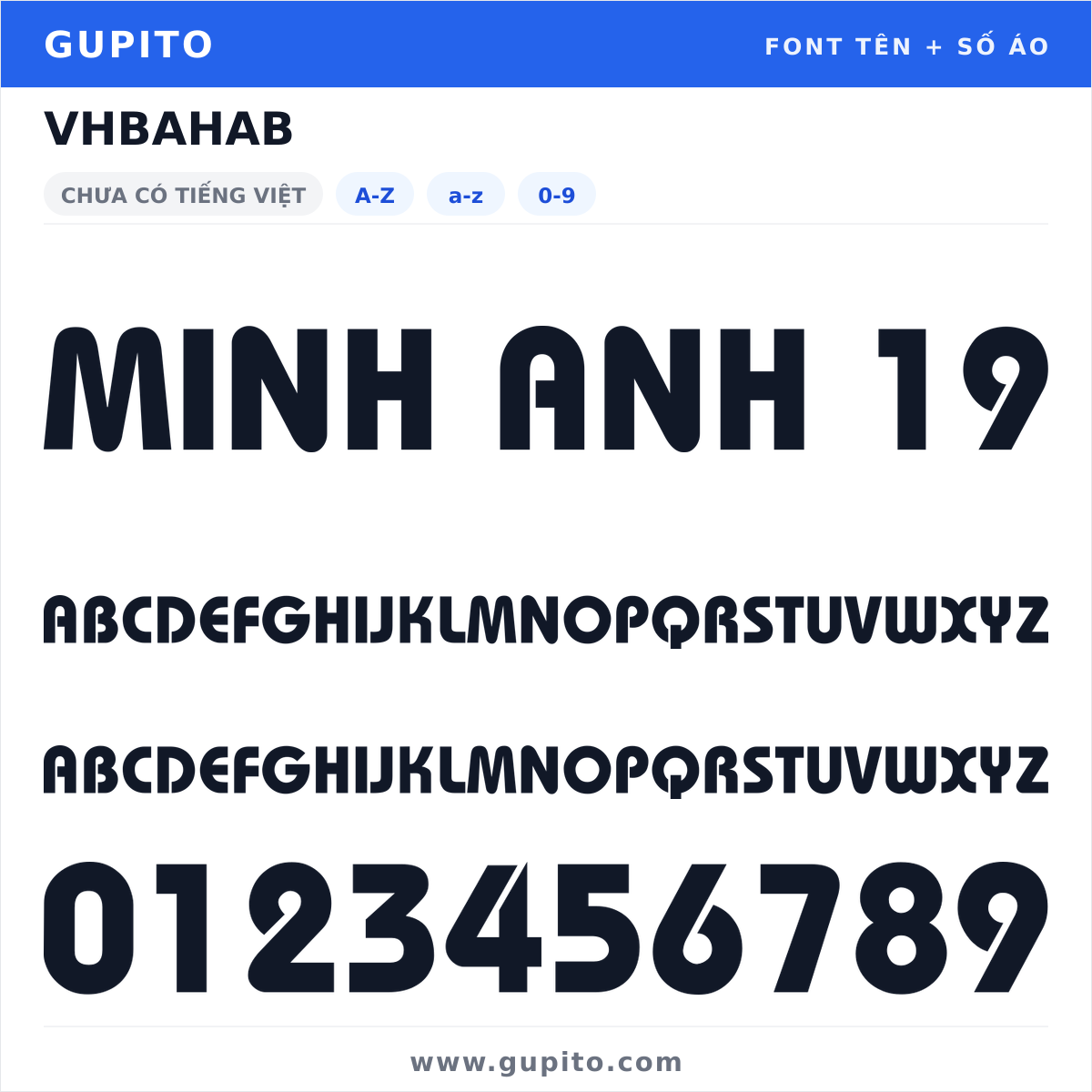
.VnBahamasBH Bold
.VnBahamasBH Bold · Font VHBAHAB in tên số áo thể thao, font chữ in chuyển nhiệt · thể thao bo tròn
Font VHBAHAB với nét chữ đậm, bo tròn, phong cách thể thao, có bảng số 0-9. Phù hợp in tên áo bóng đá, áo lớp, quà tặng. Bộ chữ .VnBahamasBH Bold dùng để in chuyển nhiệt lên áo đấu, áo lớp, áo nhóm và đồ thể thao theo yêu cầu. Kiểu dáng: thể thao bo tròn. Font dùng cho chữ không dấu và số áo. Có đủ bộ chữ số để in số áo. Từ khoá liên quan: font vhbahab, font in ten ao, font in so ao, font the thao, font chuyen nhiet, font co bang so, font chu thuong, font chu hoa.